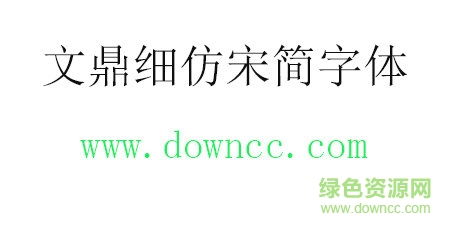
文鼎细仿宋简字体是一款笔画细腻的中文简字体。该字体的给人的感觉像有点倾斜样,有种飘逸感,适合写小说或者大篇幅文章的朋友使用,能够让你的文章更加具有个性魅力,感兴趣的朋友就快来绿色资源网下载使用吧!
文鼎细仿宋简字体的主要特点是方正雅观,结构条理清晰,字符覆盖面广,覆盖了绝大部分的汉字,包括一些生僻字,且小字体清晰,小而不失字体特点,是设计中被广泛使用的字体。